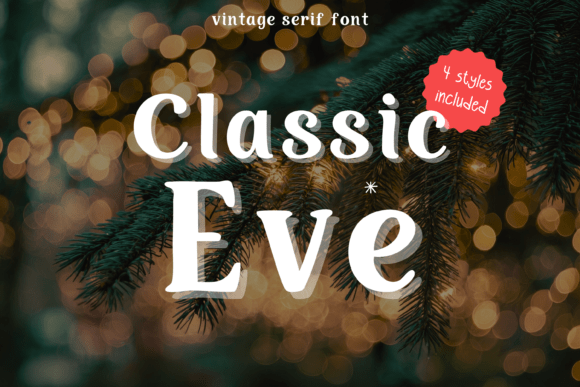
Classic Eve
Classic Eve – La police vintage qui fait briller vos projets de Noël
Vous cherchez une typographie qui capture l’essence chaleureuse et rétro des fêtes de fin d’année ? Classic Eve est la réponse. Conçue spécialement pour les créateurs qui veulent insuffler un esprit de Noël authentique à leurs designs, cette famille de polices à empattement allie élégance classique et charme festif.
Pourquoi choisir Classic Eve ?
- Design vintage & sérif – Les lettres aux courbes douces rappellent les cartes de vœux d’antan, parfaites pour une ambiance nostalgique.
- Lisibilité optimale – Même en petite taille, les caractères restent clairs, idéaux pour les tags cadeaux et les invitations.
Utilisations idéales de Classic Eve
- Cartes de vœux et étiquettes cadeaux personnalisées
- Invitations de mariage d’hiver au style rétro
- Créations Cricut & Silhouette : décorations de sapin, guirlandes, stickers
- Visuels pour les réseaux sociaux : posts Instagram, stories, bannières Facebook
- Lettrage Procreate : illustrations manuscrites festives
- Branding rétro pour boutiques en ligne et papeterie
- DIY crafts de Noël : boules, cartes pop‑up, papiers cadeaux
Points forts à retenir
Avec Classic Eve, chaque projet gagne en authenticité festive. Son style vintage séduit les amateurs de design traditionnel tout en restant suffisamment moderne pour les plateformes numériques. Que vous prépariez une campagne marketing de fin d’année ou un simple bricolage de Noël, cette police apporte la touche magique qui fait toute la différence.
Conclusion – Le must‑have de la saison